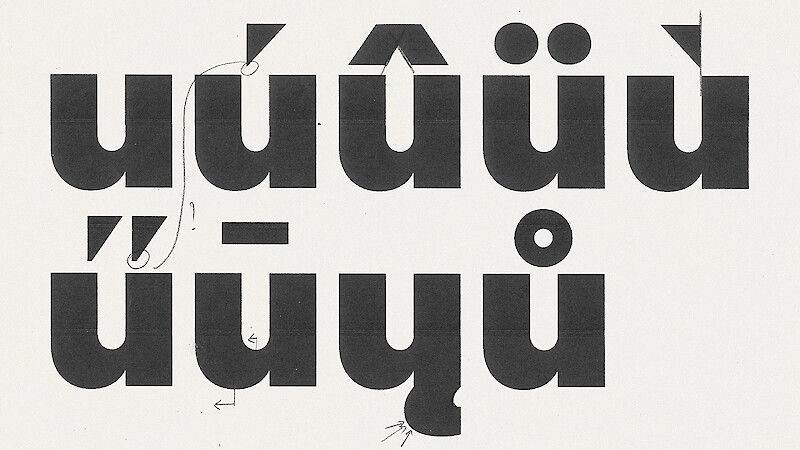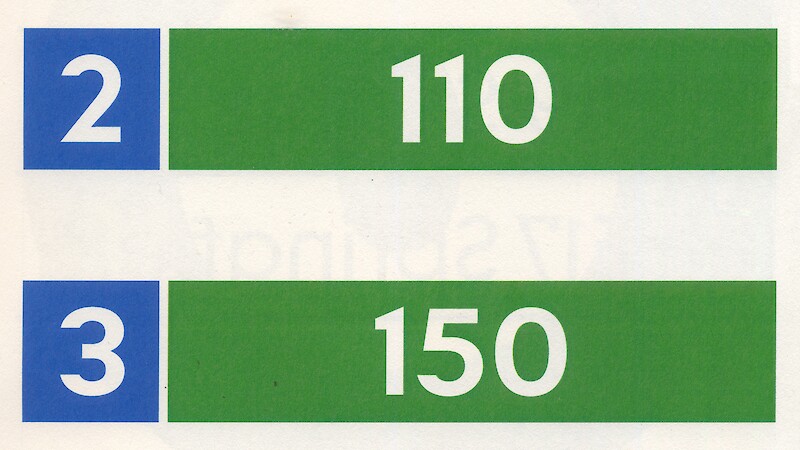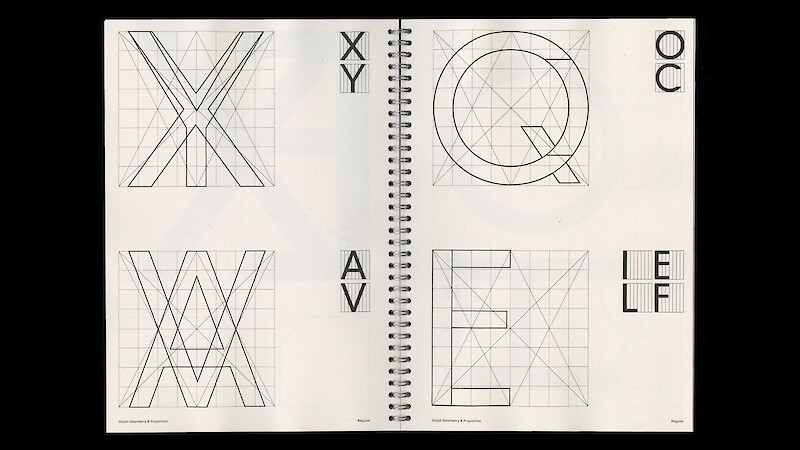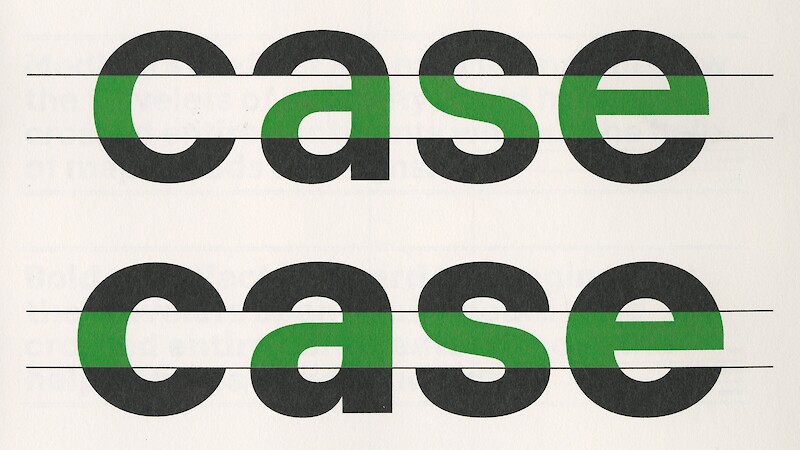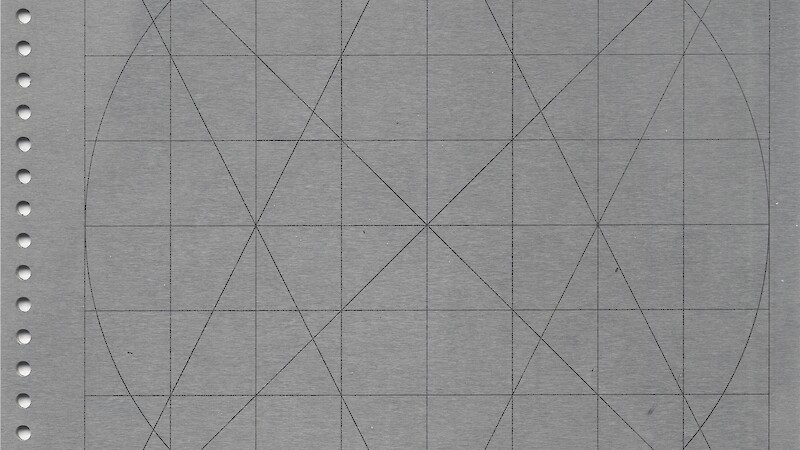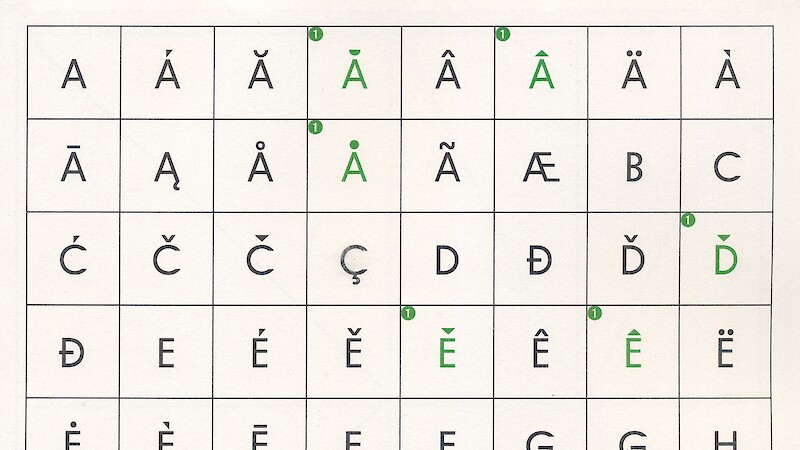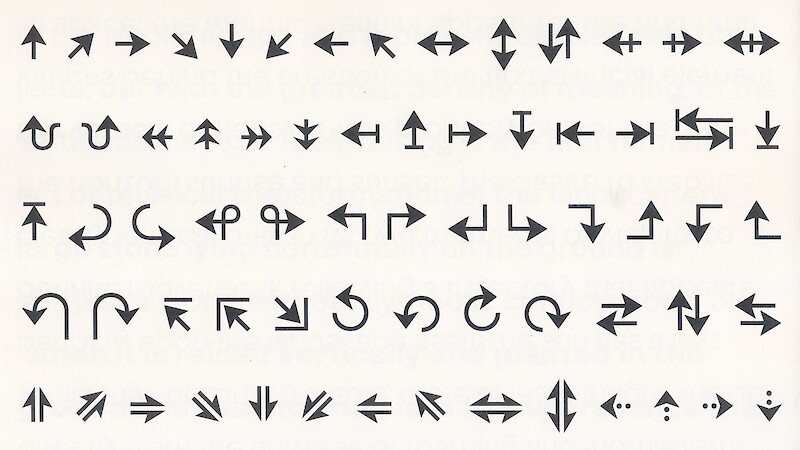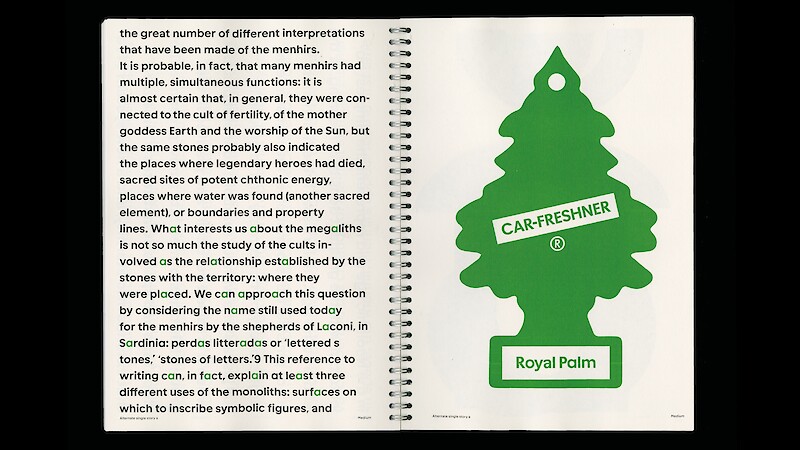
Itera – der Weg der Schrift
Die Typografie der Wegführung ist entscheidend dafür, wie wir mit unserer Umwelt interagieren. Das Lesen gibt uns die Möglichkeit, uns mithilfe der gewonnenen Information gezielt in vorhandenen Räumen zu bewegen. Entsprechend kann die Typografie mit ihrer Umgebung interagieren. Wie können Bewegungen ein Schriftbild und seine Lesbarkeit beeinflussen? Richtung, Abstand und Geschwindigkeit sind Schlüsselfaktoren dafür, wie man Text wahrnimmt. Diese Parameter bestimmen die Gestaltung des Schriftbildes und wirken sich auf die Proportionen der Buchstaben aus. Das Schriftbild kann sich unterschiedlichen Gegebenheiten anpassen und ist in der Lage, mit Bewegungen im Umfeld zu interagieren. Das Projekt basiert auf Eisenbahnschriften und bezieht die Natur der groben Gitterstruktur, gepaart mit menschenähnlichen Bewegungen, mit ein.
Samara Keller